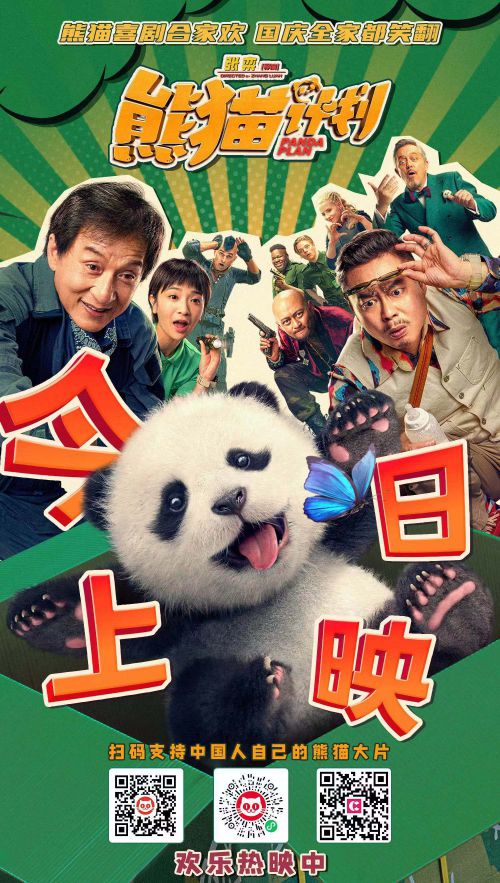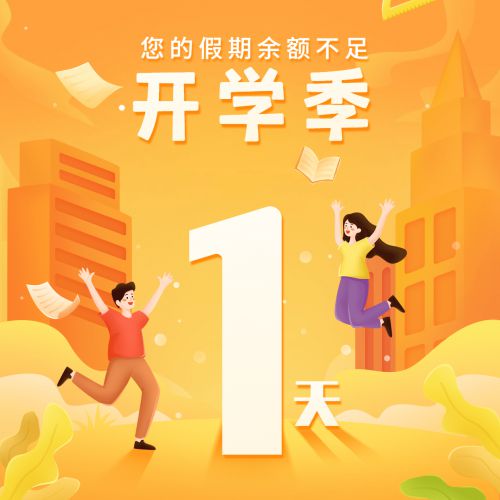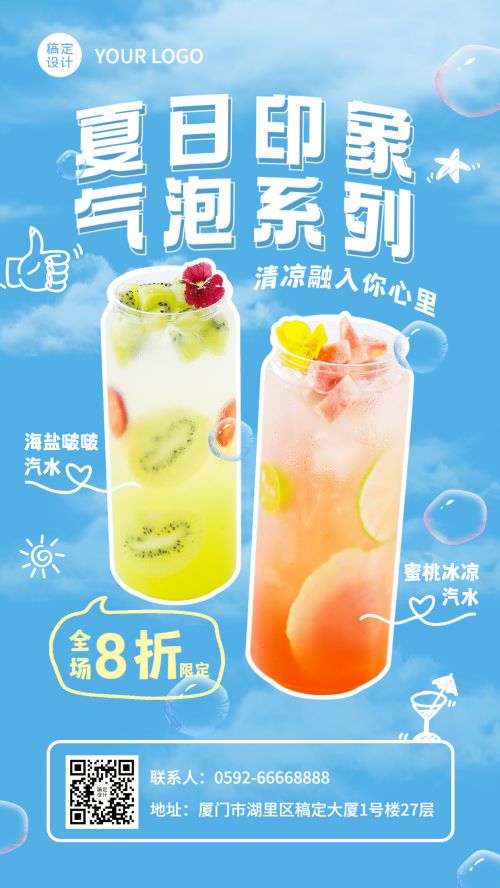
点字匹喏曹
点字匹喏曹字体童趣盎然、个性强烈,有着浓郁诙谐可爱的气息。点字匹喏曹笔画的穿插生动,粗细形态有着内在变化,简洁的笔形给人活泼而不失稳重之感。所有笔画端头圆润处理让字形更加个性鲜明,生动有趣,同时也极具亲和力。
卢鑫亚
90后字体设计师,曾获第二届字体之星评委奖,最具商业潜力奖,第三届字体之星评委奖。